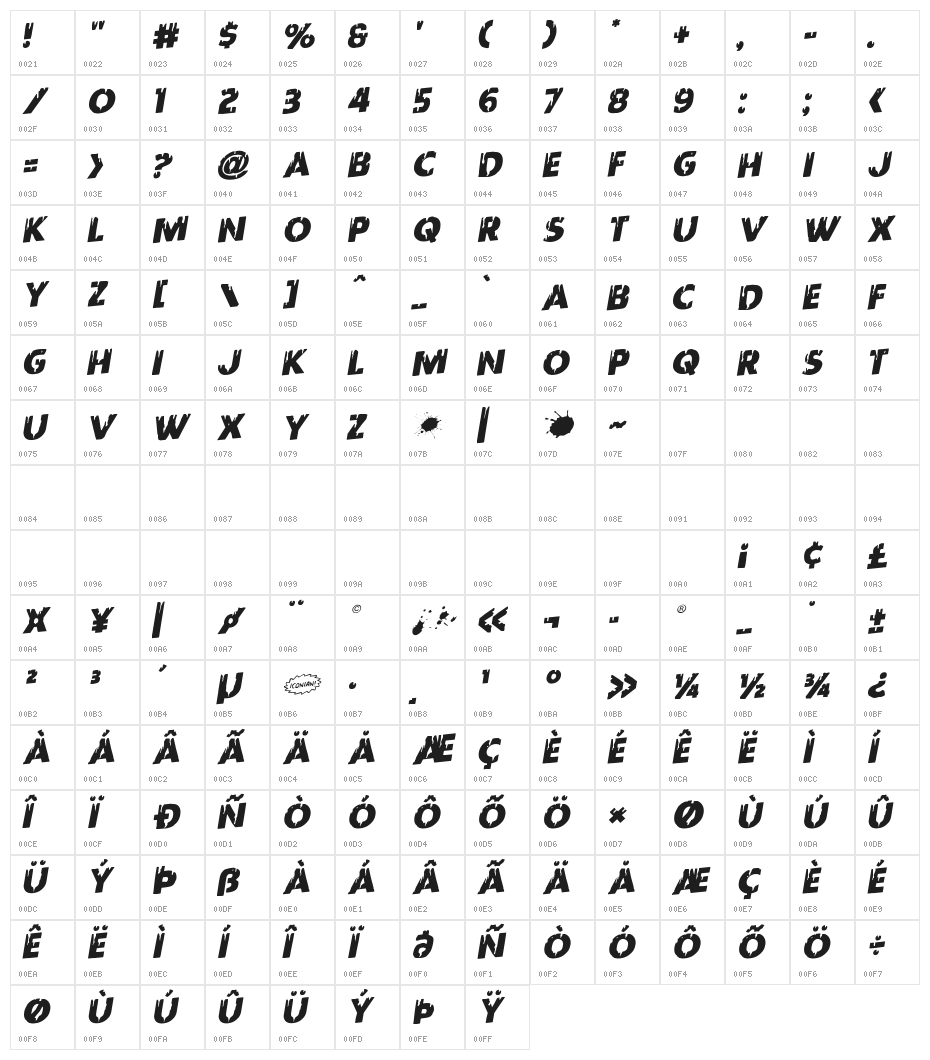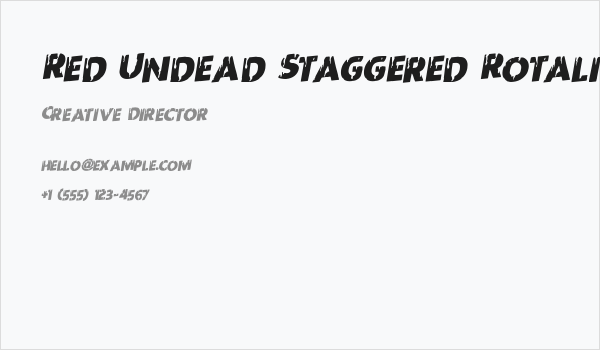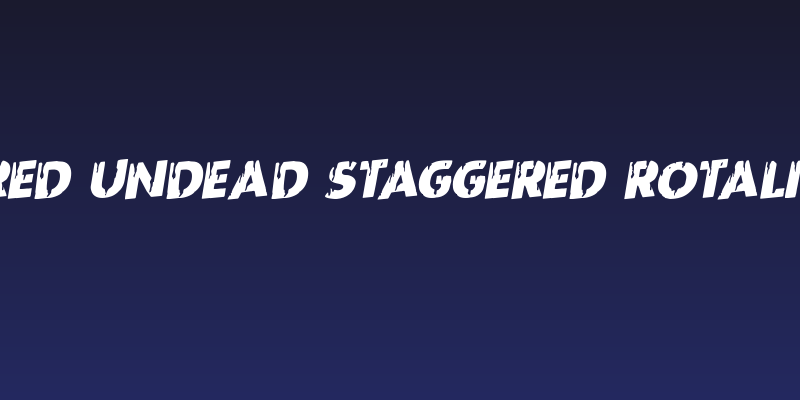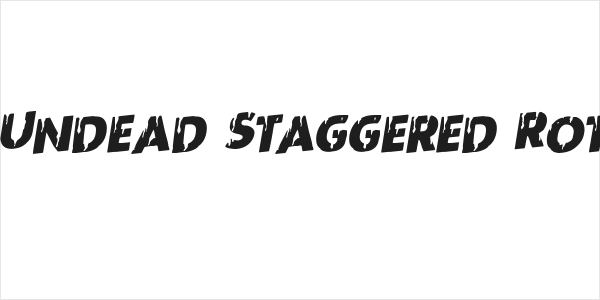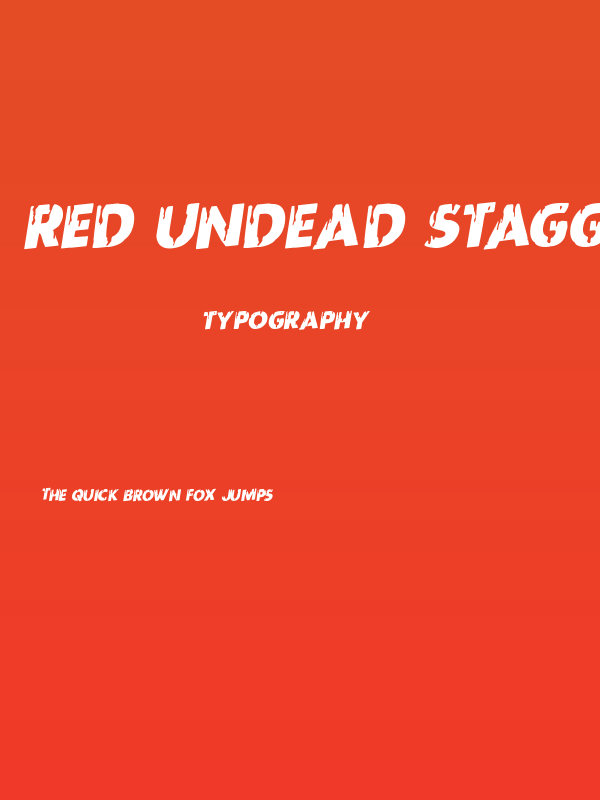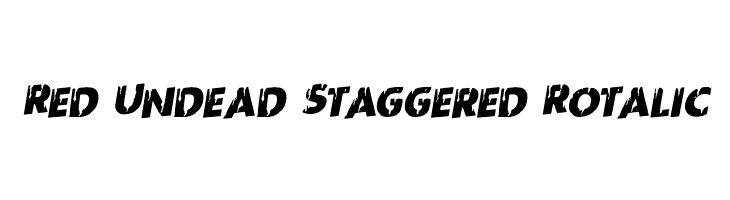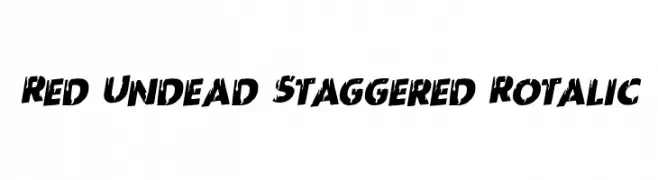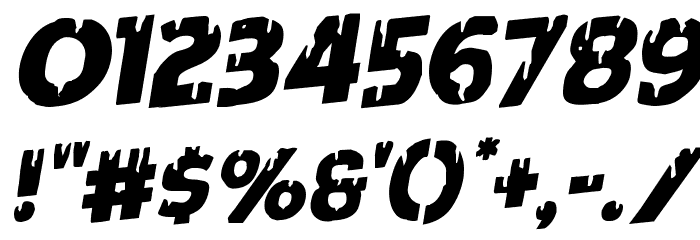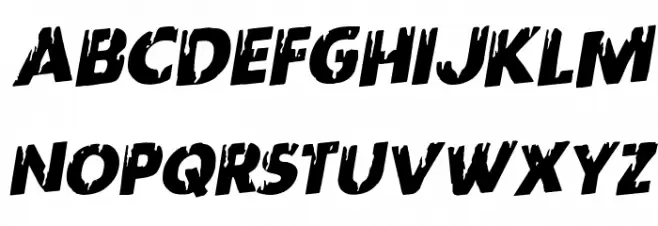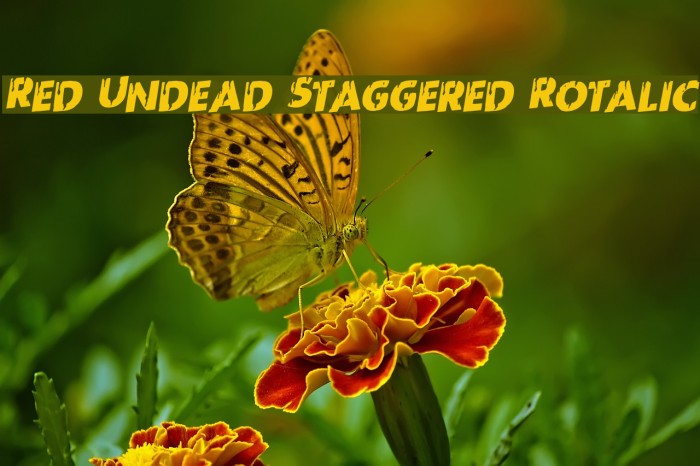
Red Undead Staggered Rotalic Font
| Progetti proposti | Ideal for posters, album covers, video game titles, and any project needing a bold, edgy look. |